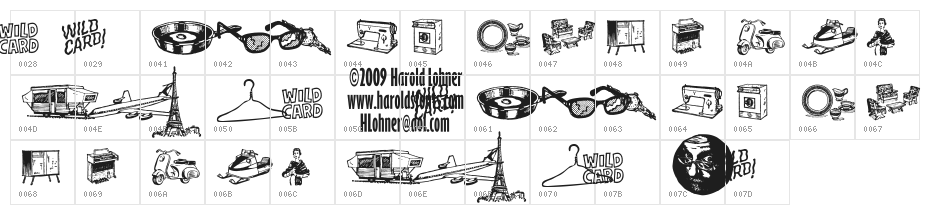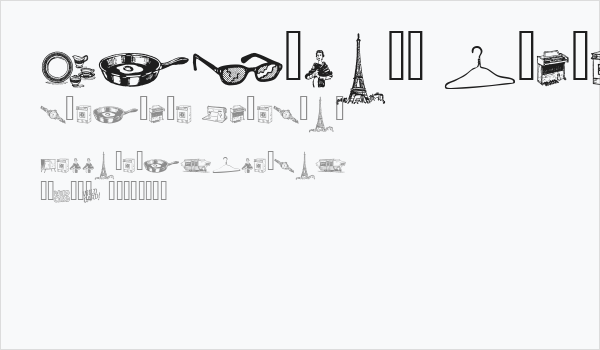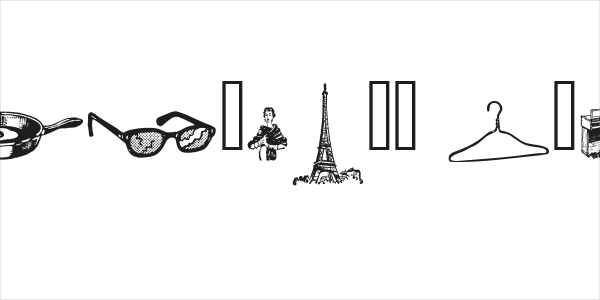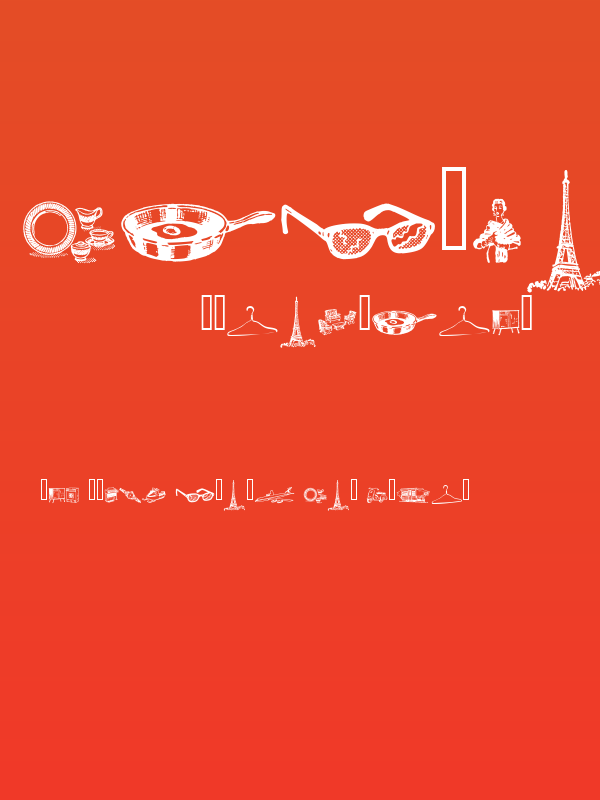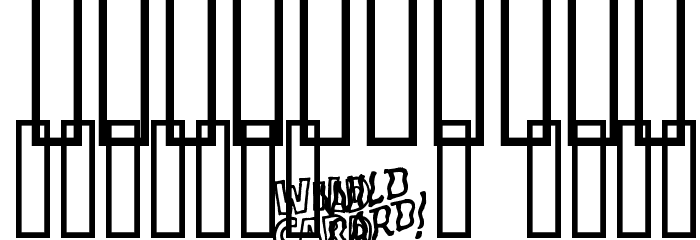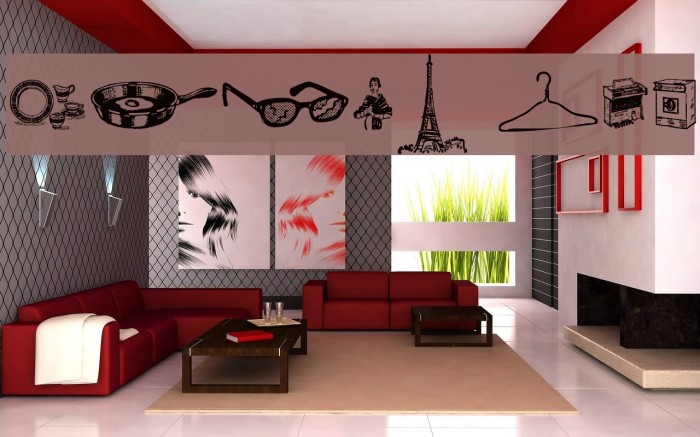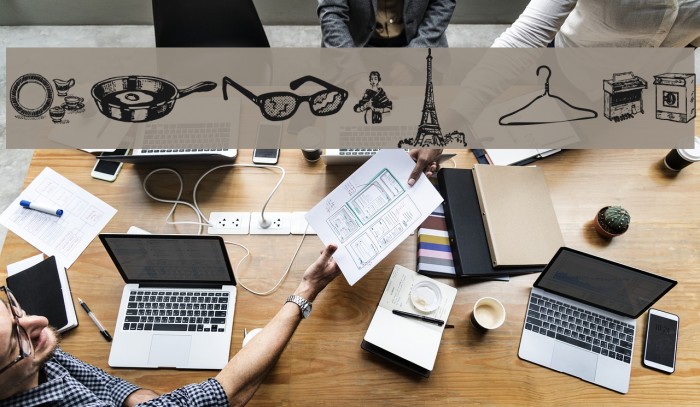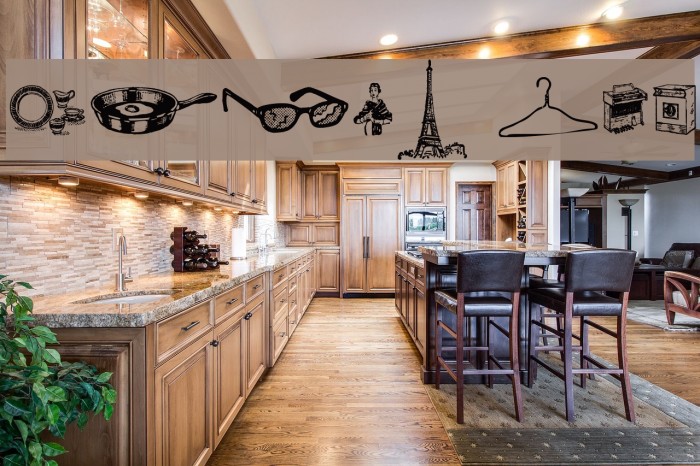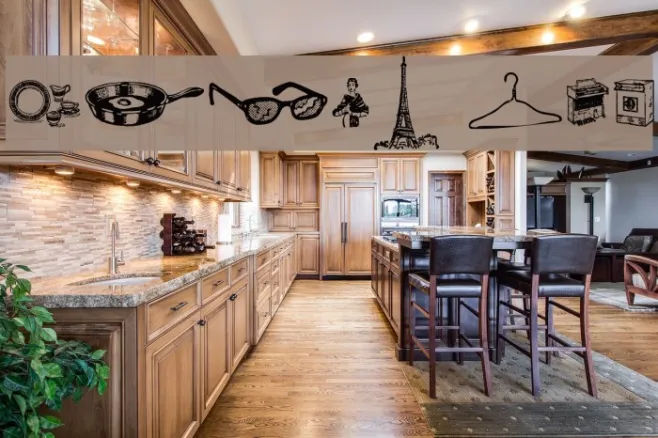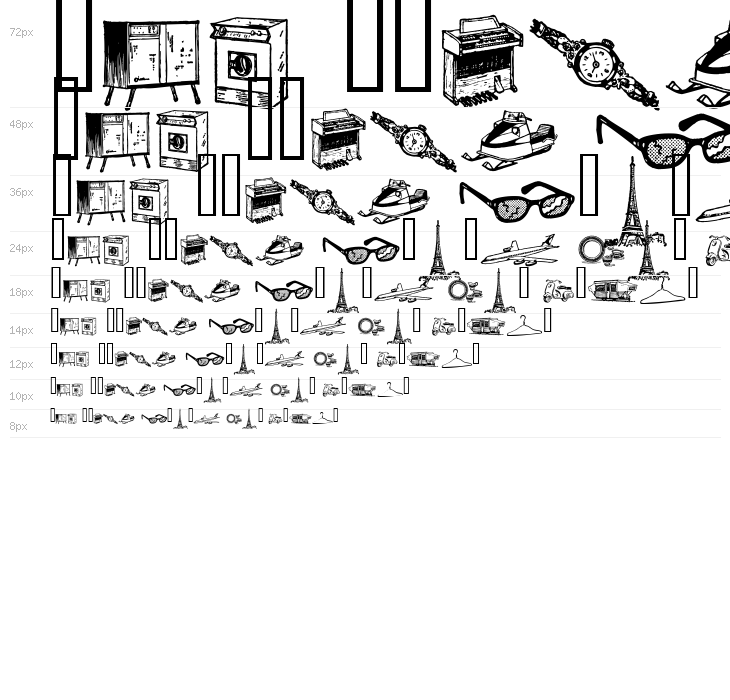
Fabulous Prizes Font
| Style général | Decorative, Whimsical, Playful |
| Cas d'utilisation | Headlines, Posters, Themed graphics, Logos |
| Projets proposés | Game shows, event posters, playful branding, children's materials, novelty invitations. |